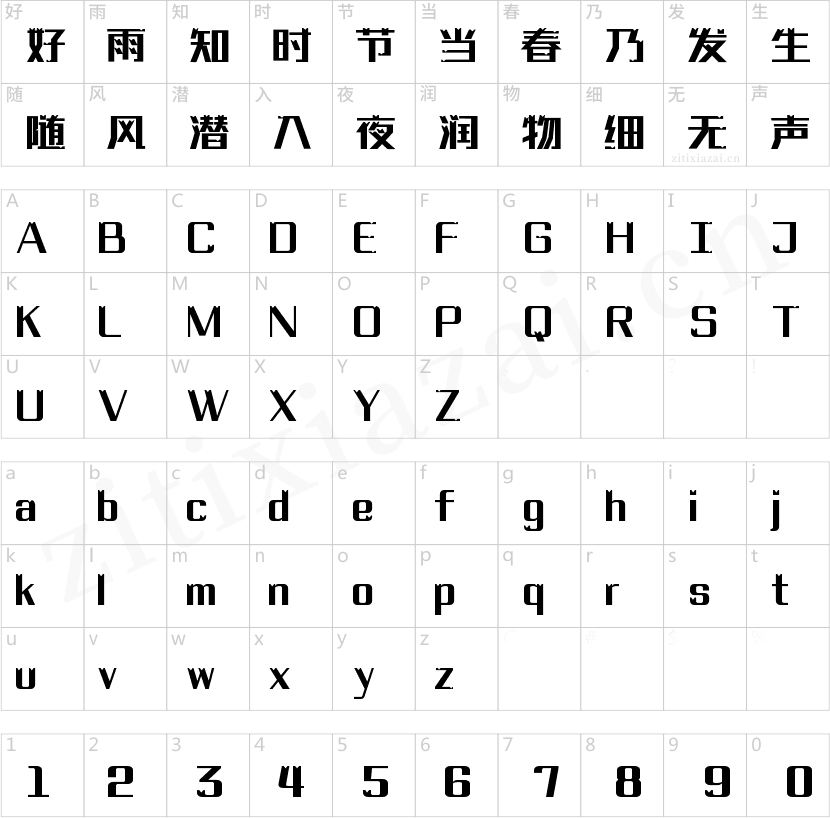
字魂彩虹积木体
字魂彩虹积木体,这款字体结构工整、笔画清晰,兼顾美观与易读性,适用于标题、正文、海报、包装、LOGO 等多种场景。字形优雅稳定,风格百搭耐看,适配日常排版与创意设计,让文字呈现更舒适、更具质感。字魂彩虹积木体一笔一画,皆是细节,以均衡的比例、流畅的线条打造舒适视觉体验,字形端正大气,风格简约现代。无论是商业设计、品牌宣传还是日常排版,都能轻松驾驭,让文字更有格调与力量。字魂彩虹积木体字体下载。
字魂字体字小魂彩虹积木体字体是由字魂创意字库设计并生产的一款可商用的字体,被收录于字小魂系列。该字体支持GB-2312标准,包含6763个中文、字母、符号和数字,字体类型偏向创意字体,具有活泼、动漫、时尚的风格,在市面上广泛用于印刷品&包装、活动促销、海报企宣等场景。